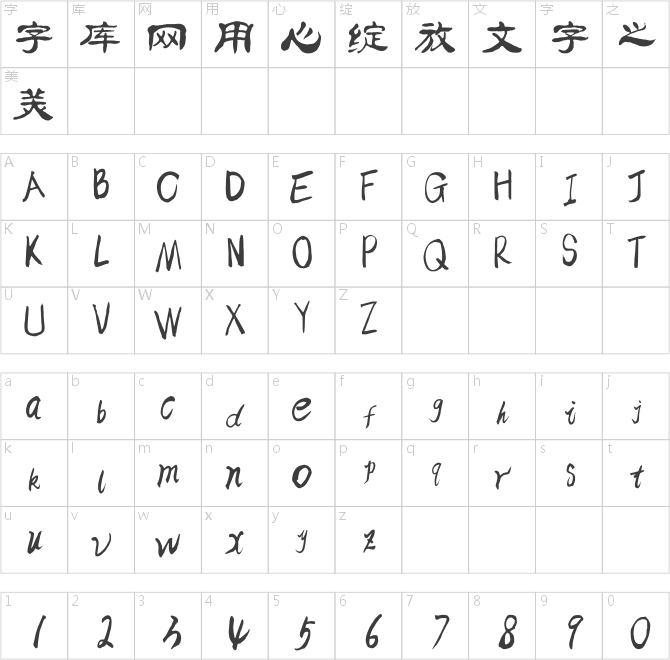
逐浪簡明新隸體 詳情頁
字體名稱: 逐浪簡明新隸體
逐浪簡明新隸體
一款現(xiàn)代隸書,具備簡潔、大氣,又具備復(fù)古之風(fēng),完全符合GB2312規(guī)范。
全部手寫,再進行創(chuàng)作。
逐浪簡明新隸體字體字庫是一款讓人賞心悅目、百看不厭的中文字體,適合各類廣告和產(chǎn)品包裝設(shè)計應(yīng)用,字體大小11.32MB,格式為otf字體,上傳用戶是15331803325,作者/版權(quán)方為逐浪字庫